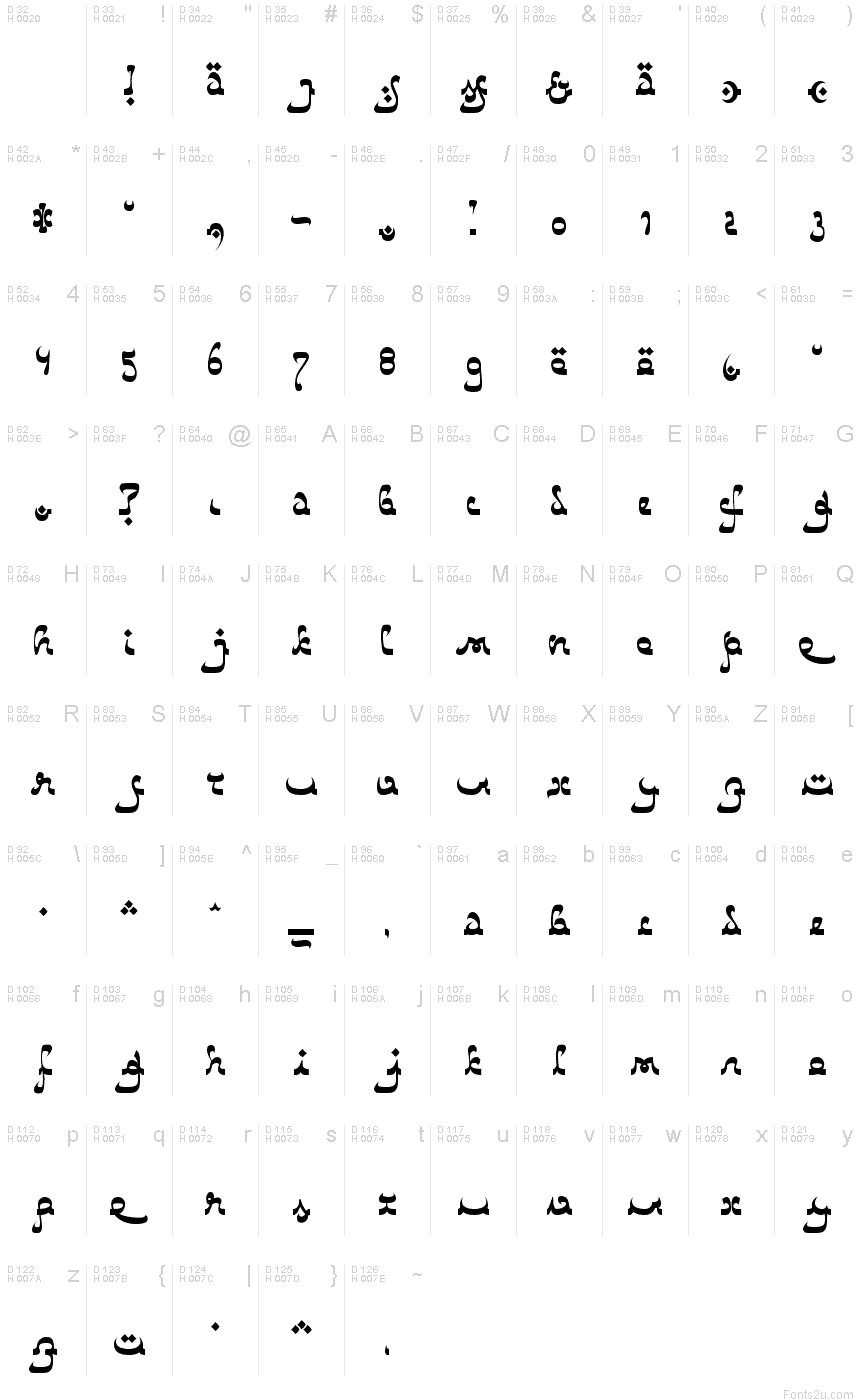
Catharsis Bedouin هو خط مجاني بجمالية مستوحاة من الطراز العربي. تلتف ضربات الحبر فيه وتتداخل مثل شريط مستمر، مما يضفي على الحروف اللاتينية طابعاً يدوياً دخانياً مليئاً بالأجواء الساحرة. إيقاعه الحر وغير المنتظم يمنح العناوين طاقة بدوية جوالة تتبادر إلى الذهن فوراً بـ "الشرق الأوسط" دون أن يكون خطاً عربياً فعلياً.
استخدم Catharsis Bedouin في تصميم العلامات التجارية للمطاعم، أو لافتات صالات الشيشة، أو ملصقات فعاليات "ألف ليلة وليلة"، أو كتيبات السفر، أو عناوين الألعاب، أو أغلفة الكتب. يتألق هذا الخط المجاني عند استخدامه بأحجام كبيرة، حيث يمكن لمنحنياته المنسابة وأشكاله السوداء الكثيفة أن تتنفس حقاً؛ ادمجه مع خط بلا زوائد (sans serif) هندسي ونظيف للنصوص الأساسية للحفاظ على القراءة المريحة والتوازن.